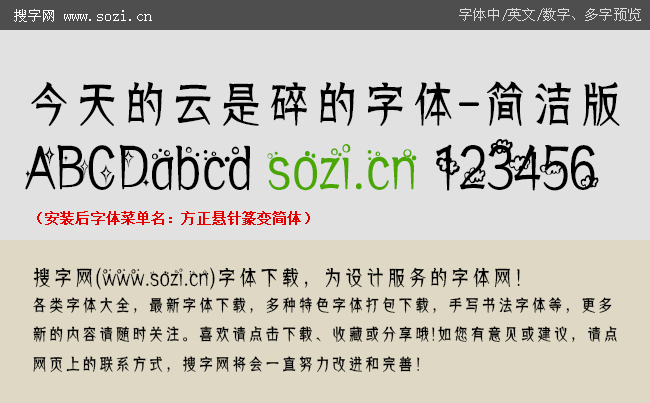
今天的云是碎的簡潔版
搜字網(wǎng)給大家提供一款今天的云是碎的簡潔版手機(jī)中文字體下載。這款手機(jī)字體是在方正懸針篆變簡體為原形。對數(shù)字和英文進(jìn)行了裝飾,方正懸針篆變字體意在保留篆書韻味,同時(shí)將隸書與楷書筆畫特征熔于一爐,端莊秀美、開張疏朗,雍容大氣、復(fù)古卻易讀。特別適合喜歡手機(jī)字體個性一些的朋友在手機(jī)上安裝使用。